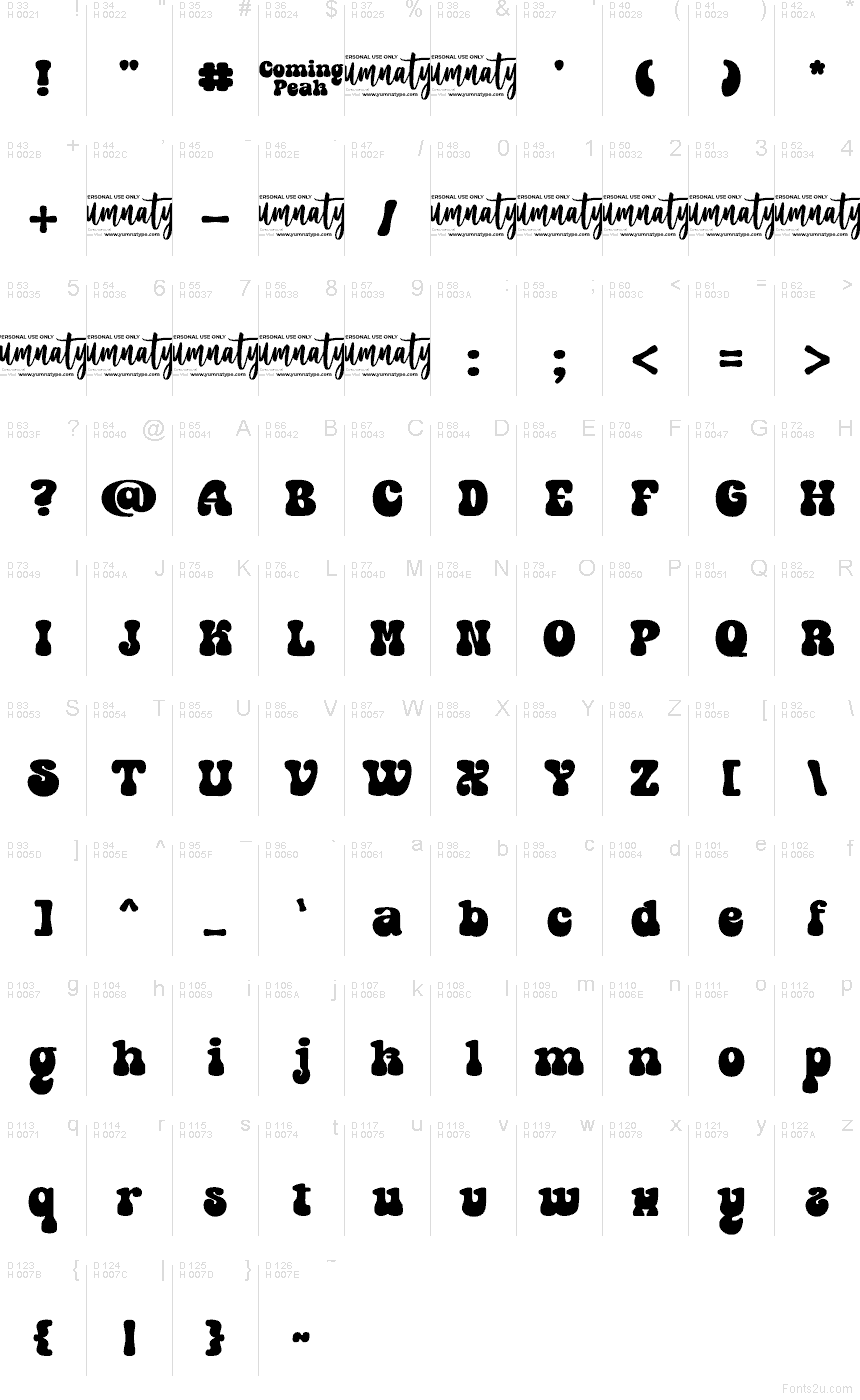
Coming Peak od Yumnatype je bezplatné groovy display písmo tvarované velkými, nadýchanými siluetami a jemnými zářezy, které písmenům dodávají pohyb připomínající lávovou lampu. Díky zaobleným horním částem, hlubokým křivkám a kompaktní hmotě je tento styl zakořeněn v estetice plakátů ze 70. let, spíše než v generickém „bublinkovém“ písmu.
Tento hustý a plynulý tvar dodává krátkým titulkům jasnou roli na obalech alb, letácích, značkách kaváren, designech samolepek a příspěvcích na sociálních sítích, které potřebují hřejivý retro nádech. Hodí se také pro obaly a nadpisy, kde nafouknutý rytmus písma unese sdělení i bez nutnosti další dekorace.